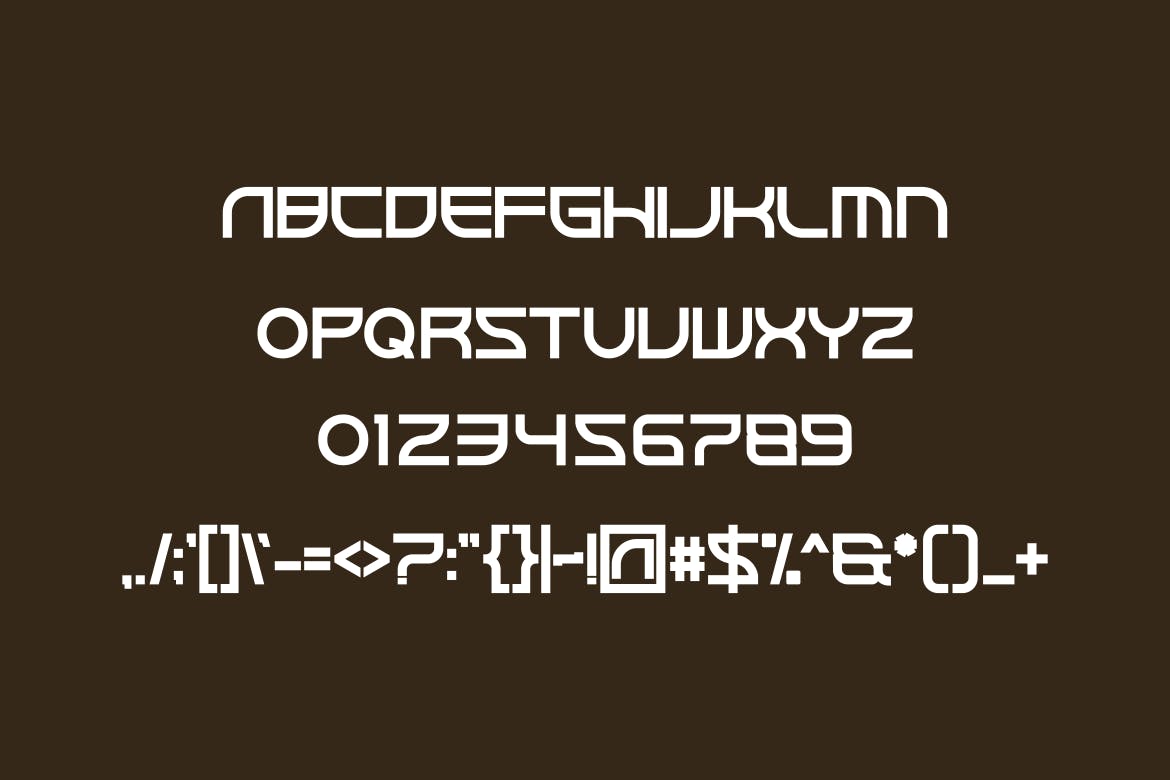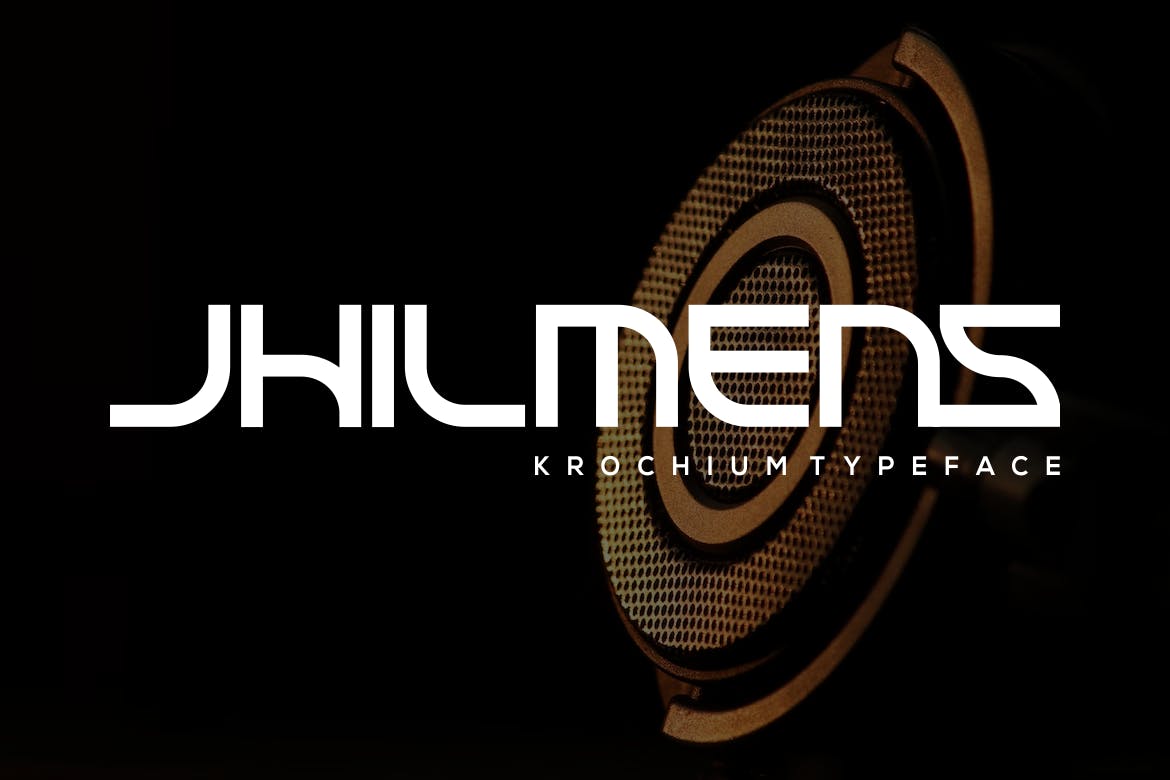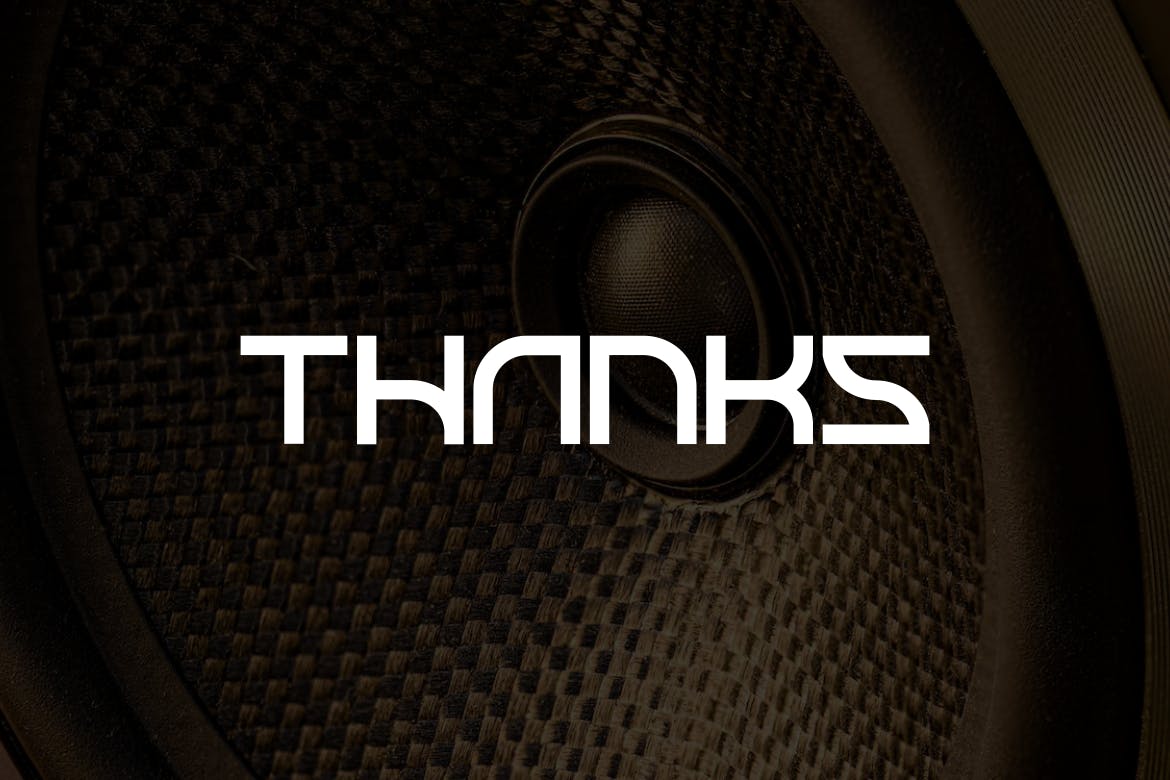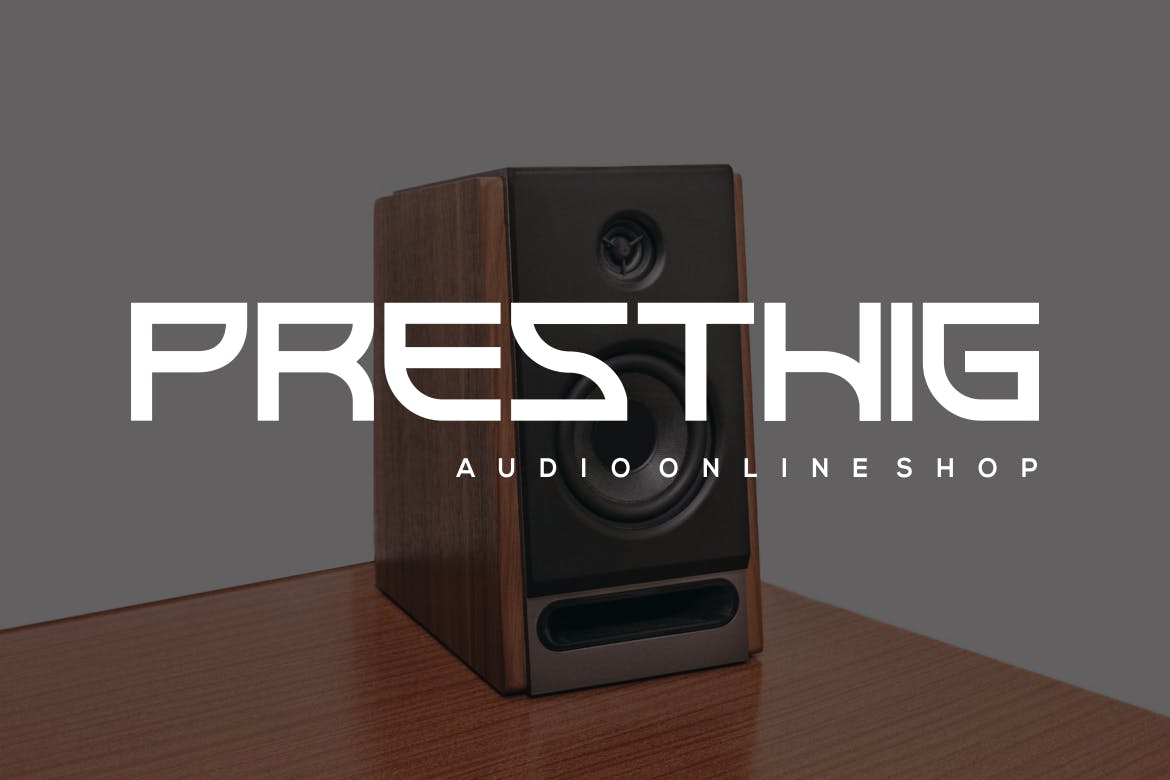
دانلود فونت مدرن کروکیوم - Krochium
Krochium Modern Font
فونت مدرن کروکیوم، انتخابی ایده‌آل برای پروژه‌های طراحی شما!
معرفی محصول جدید ما Krochium - فونت مدرن
Krochium - فونت مدرن یک فونت نمایشی بولد و اصیل است. این فونت مناسب برای هر پروژه برندینگ مانند لوگو، چاپ تیشرت، ورزش‌های الکترونیکی و بسیاری موارد دیگر می‌باشد و در انواع زمینه‌ها برجسته است.